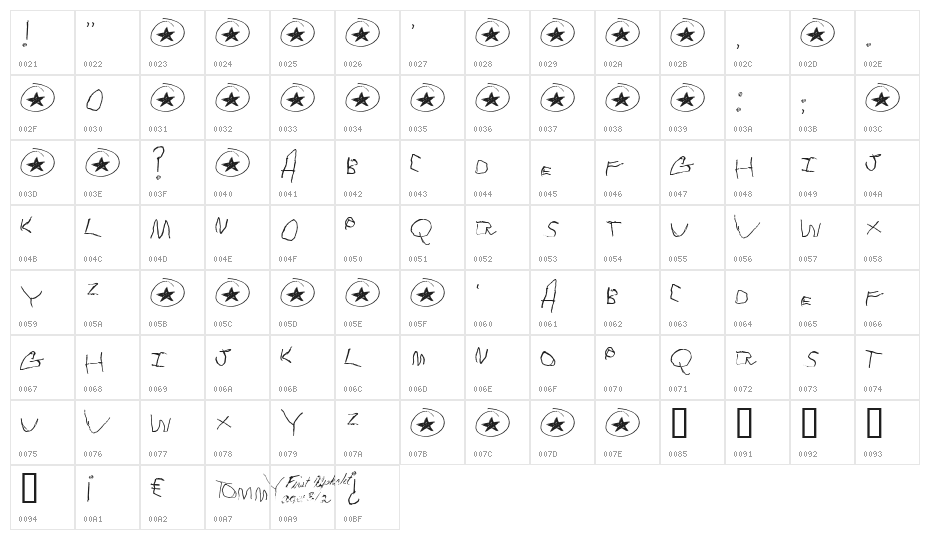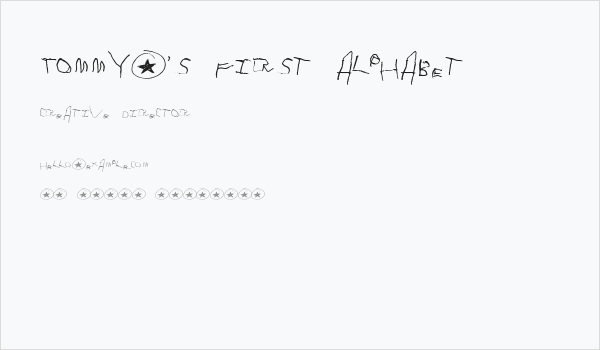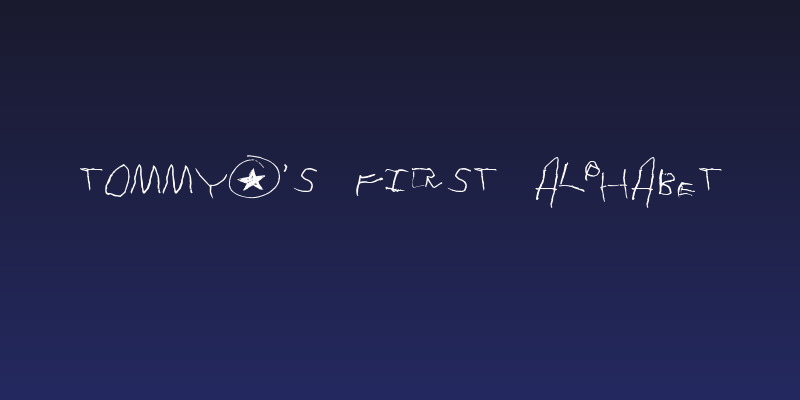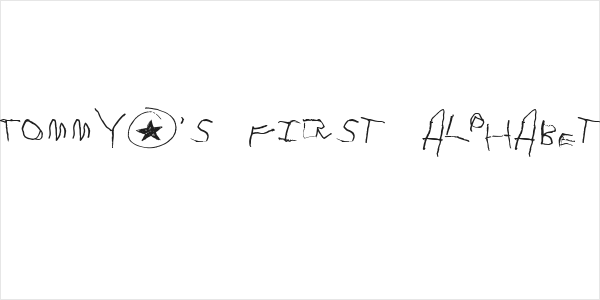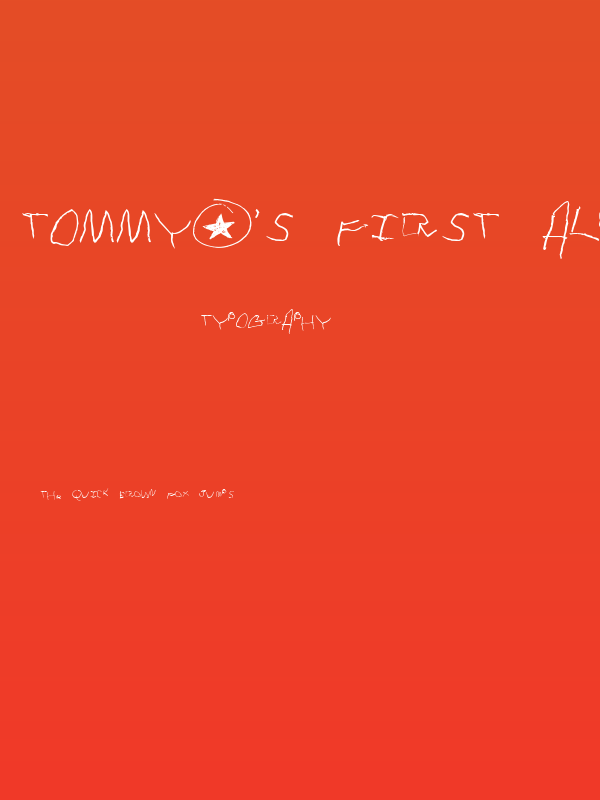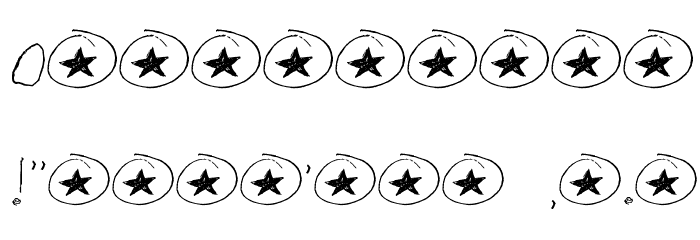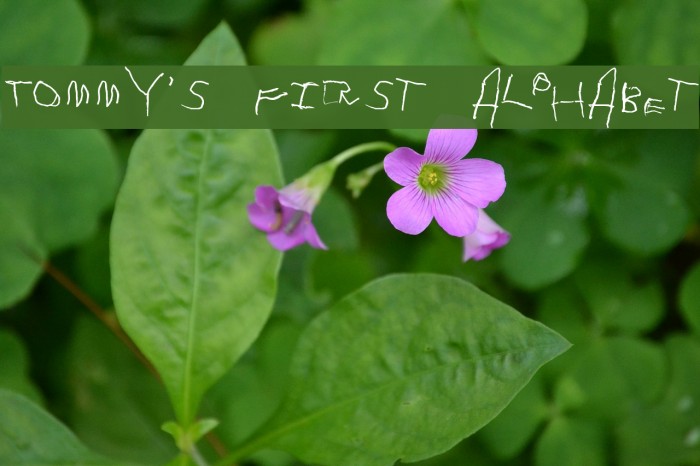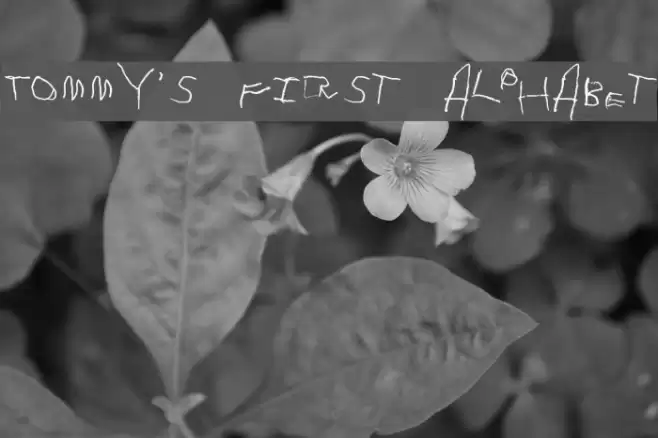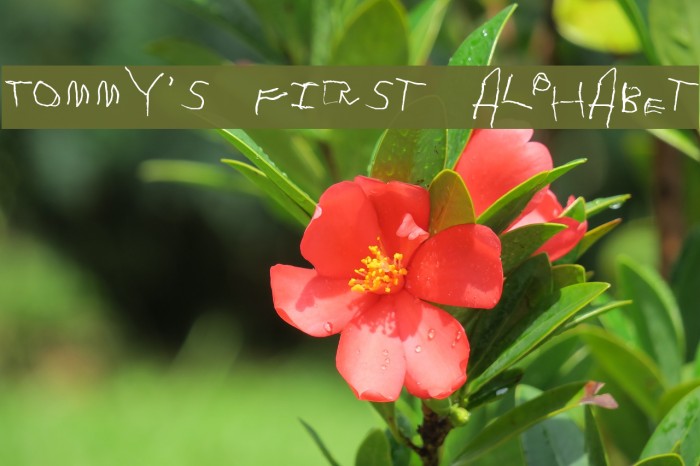
Tommy's First Alphabet Font
| Style général | Playful, Childlike |
| Cas d'utilisation | Headlines, Creative projects, Educational materials |
| Projets proposés | Ideal for children's books, educational materials, playful branding, and creative projects that require a whimsical touch. |